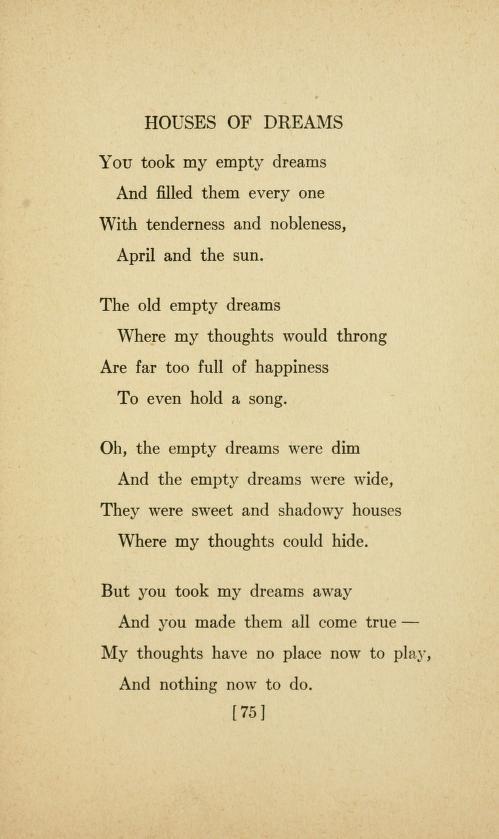
Suche Schrift dieses amerikanischen Buches von 1921 (Joseph Browning, Poems)
Century bzw. Century Expanded (Morris Fuller Benton & Linn Boyd Benton, um 1900) könnten passen. Gibt es in verschiedensten Digitalisierungen. Im Bild scheint mir die x-Höhe zwar geringer als bei den digitalen Fonts zu sein. Das könnte aber auch täuschen.
Das Gedicht stammt aus:
Joseph Browning, "Poems"
Sicher?
Ich hab das im Band "Love Songs", Sara Teasdale, 1917 gefunden. Gedruckt in USA, The Macmillan Company. Das ganze Buch ist hier zu finden: https://ia802605.us.archive.org/10/items/lovesongs00teas.pdf